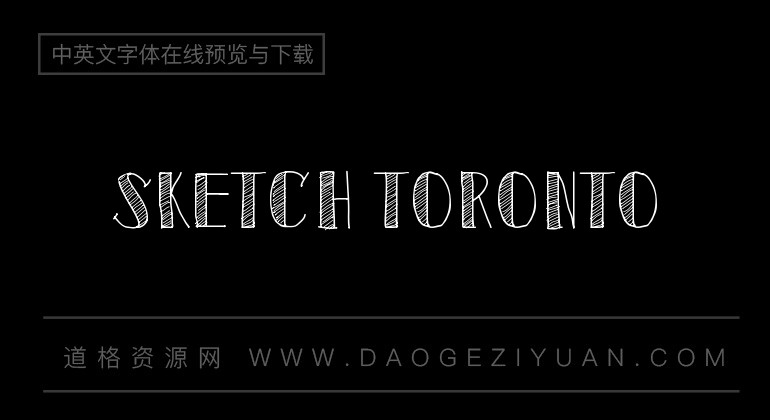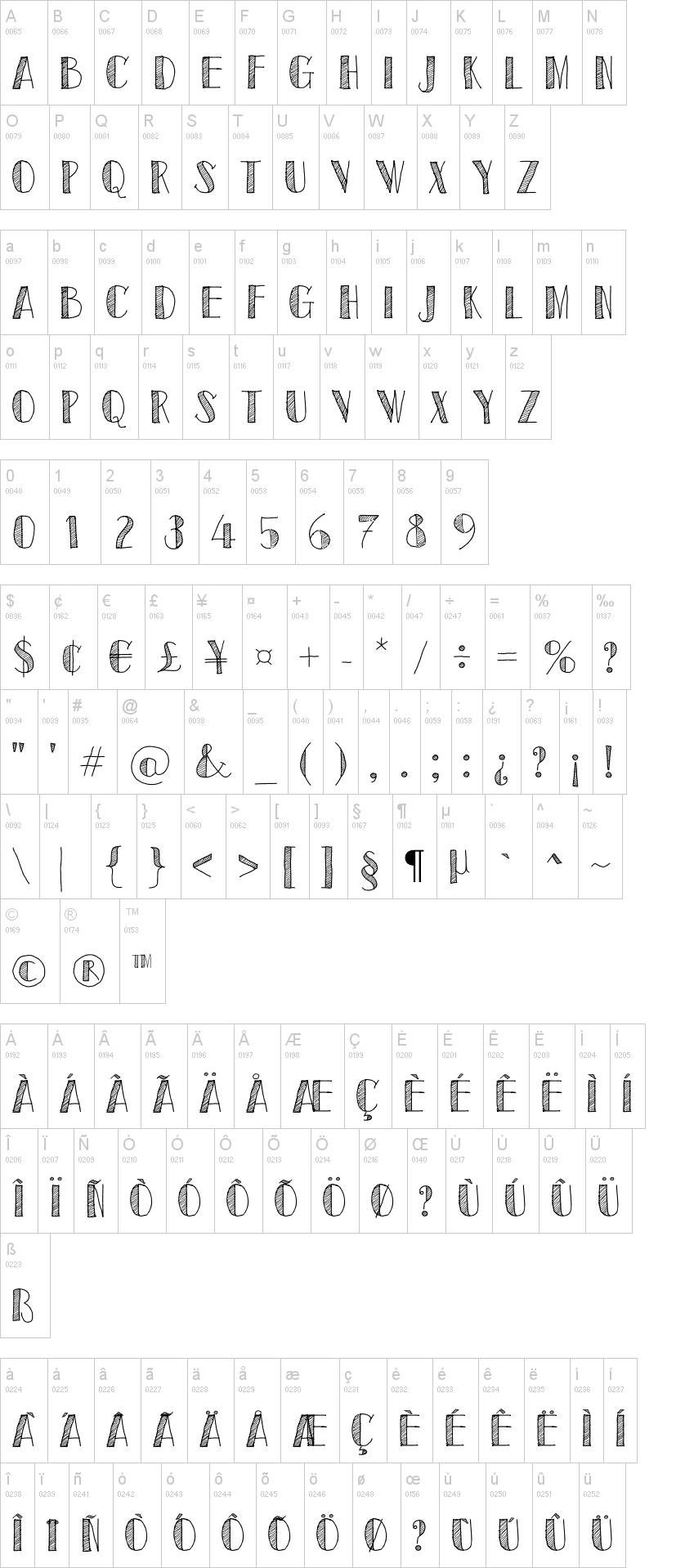
Sketch Toronto
Sketch Toronto是一款由Fontfabric字体工作室设计的简约时尚的英文字体,它的特点是笔画简洁、字形紧凑、结构规整,具有较强的表现力,可以满足不同的设计需求。它的字体风格接近于现代字体,但又有自己独特的风格,可以给设计带来新鲜感。Sketch Toronto字体支持多种格式,包括TTF,OTF,WOFF,WOFF2等,支持多语言,可以满足不同的设计需求。
Sketch Toronto是一款非常不错的手写艺术字体,具有很好的视觉感,适合于文化类的宣传设计、商业类品牌的广告和产品包装设计以及个性化文字排版等较多场景。